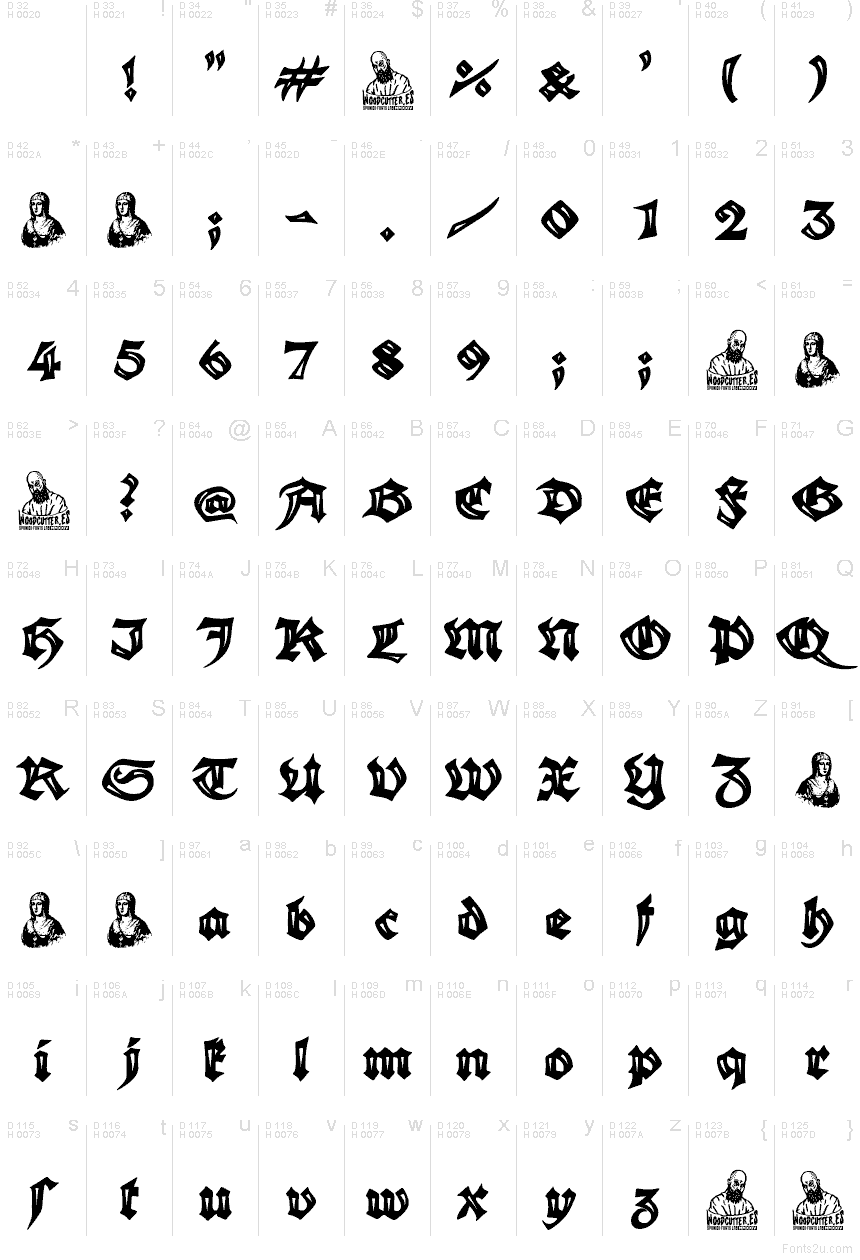
Isabella the Catholic
Isabella the Catholic, de Woodcutter Manero, é uma fonte gótica moderna e gratuita, com aquela energia característica das letras pretas e uma silhueta bruta, quase talhada. As letras apoiam-se em diagonais afiadas, cantos em gancho e aberturas estreitas, conferindo à fonte um tom medieval inquieto que evoca mais a estética de cartazes de rua do que peças de museu.
É ideal para branding de música dark, rótulos de bebidas artesanais, flyers de eventos, títulos de jogos e gráficos para vestuário que precisam de personalidade. Sendo uma fonte gratuita, também funciona muito bem em aberturas de capítulos, destaques de capas e iniciais tipo monograma, já que o ritmo angular confere às palavras curtas uma sensação de tensão, cerimônia e um toque rebelde.